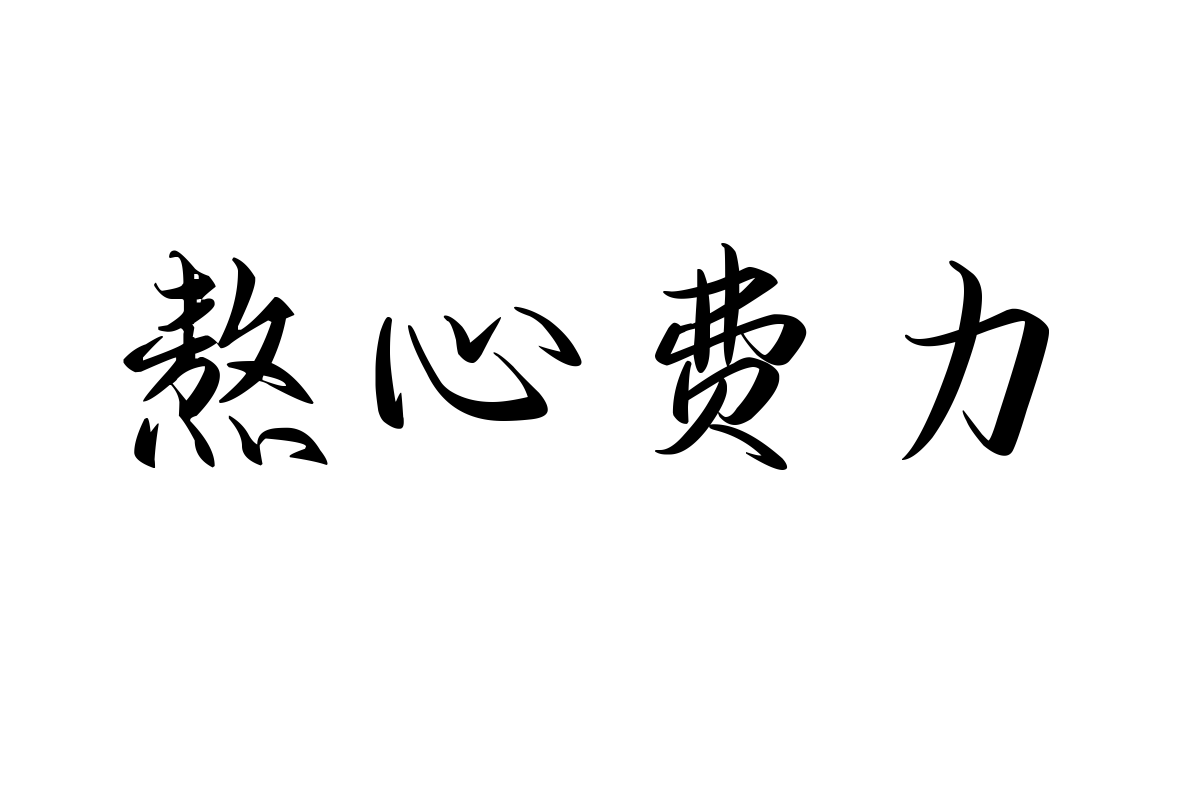
也字工厂宴山亭行楷字体是一种具有独特风格的书法字体。它的特点是笔画流畅,结构紧凑,给人一种优雅而有力的感觉。这种字体适合用于各种场合,如广告、海报、书籍等。
也字工厂宴山亭行楷字体的特点如下:
1. 笔画流畅:每个笔画都流畅自然,没有生硬或僵硬的感觉。这使得字体看起来更加美观和易读。
2. 结构紧凑:虽然每个笔画都很流畅,但整个字体的结构紧凑,没有多余的空间。这使得字体看起来更加简洁和大方。
3. 优雅而有力:这种字体既优雅又有力,给人一种强烈的视觉冲击力。这使得字体非常适合用于需要强烈视觉效果的广告和海报设计。
4. 适用于多种场合:无论是用于正式的商务场合还是轻松的休闲场合,也字工厂宴山亭行楷字体都能展现出其独特的魅力。
总的来说,也字工厂宴山亭行楷字体是一种非常优秀的书法字体,无论是从美观度还是实用性来看,都是值得推荐的选择。